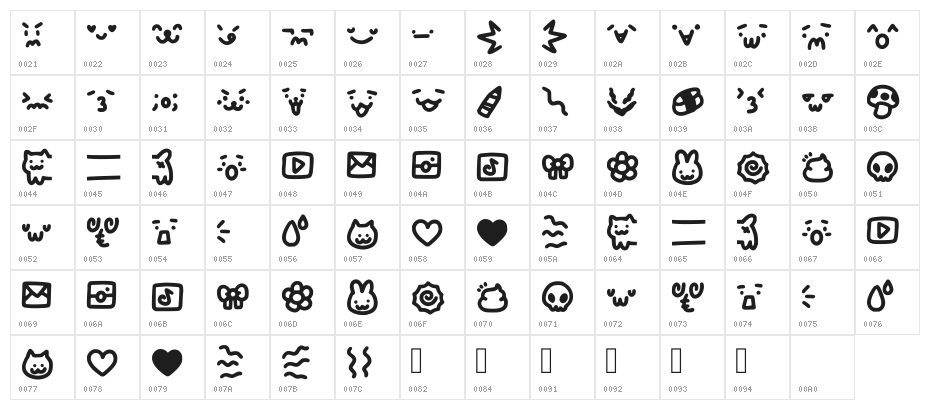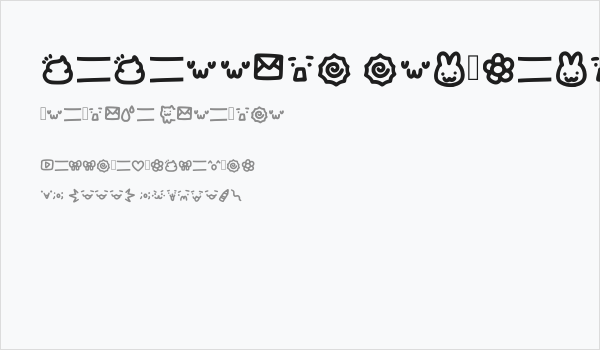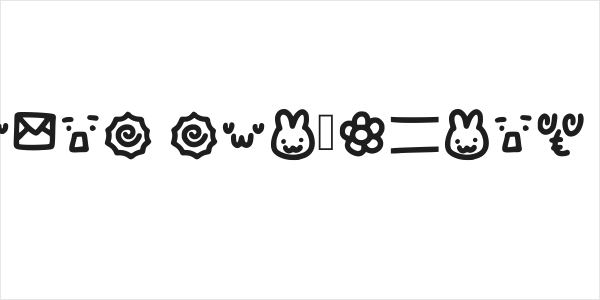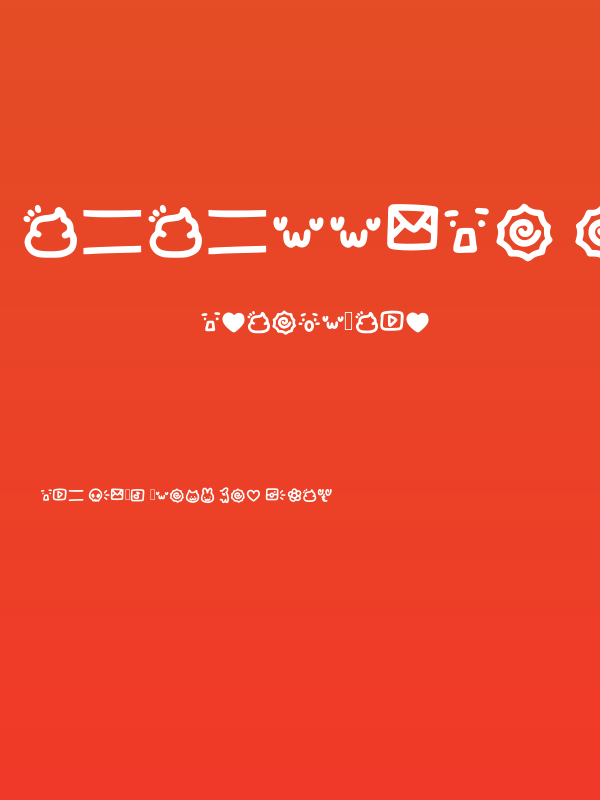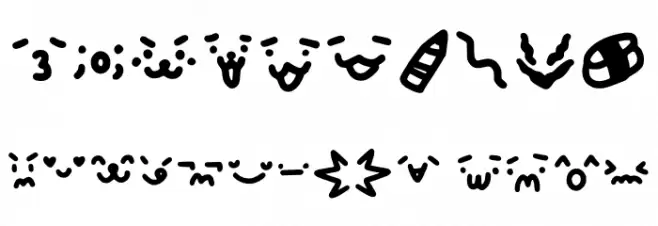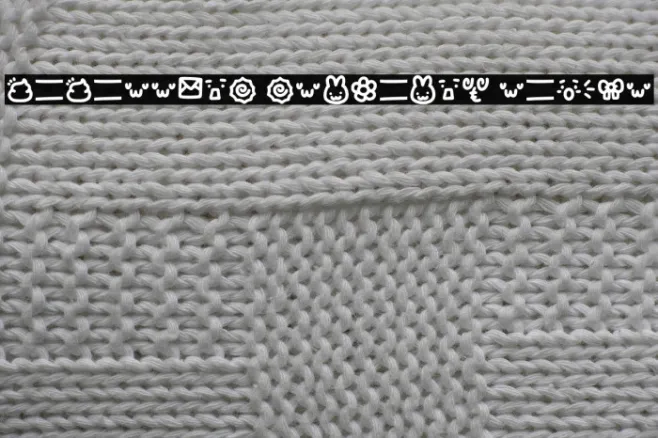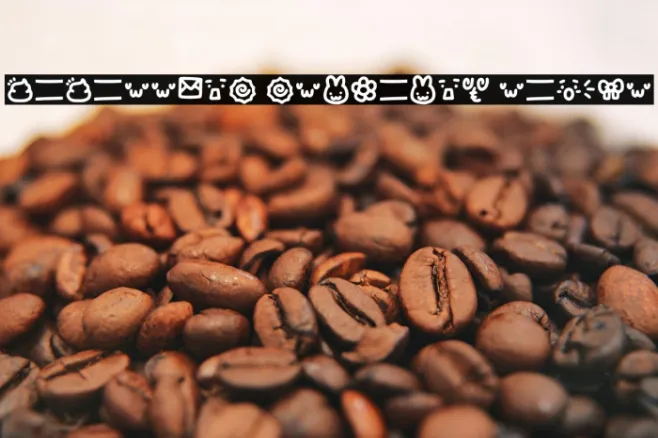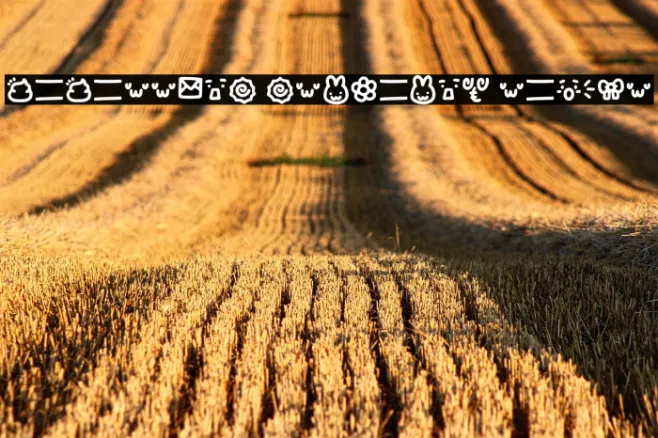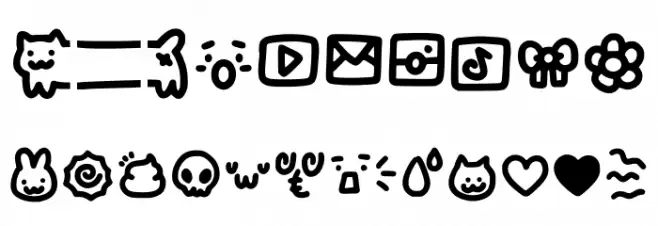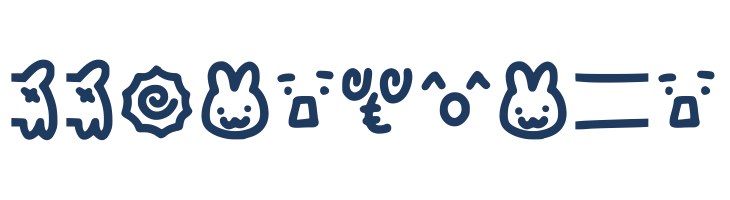
Peperrito Ornaments Regular Font
| Gesamtstil | Playful |
| Anwendungsfall | Decorative elements, Creative projects |
| Vorgeschlagene Projekte | Ideal for children's books, playful invitations, greeting cards, and creative social media graphics. |